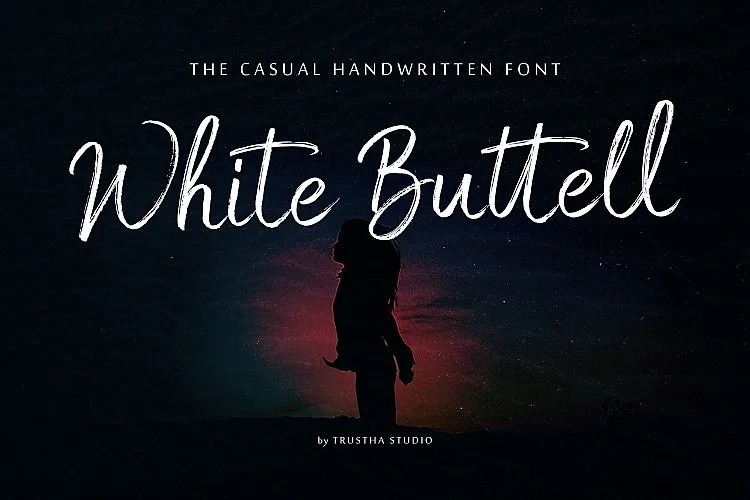
White Buttell Brush Font – Download Grátis
Olá! Aproveite essa descritiva introdução à White Buttell Brush Font. Para quem adora uma boa música, esta fonte é a perfeita melodia para seus designs, transmitindo um som mais alto ou apenas por ser incrível de se ver! Introduzimos White Buttell Font, que é uma fonte de script rascunho manual. Essa fonte tem um estilo natural da caneta secada, tornando-a perfeita para a criação de marca, anúncios, design de painéis, logotipos, capas de livros e revistas, embalagens, cabeçalhos de sites, cartões de convite, designs de roupas, produtos promocionais, campanhas de moda, newsletters, capas de álbuns e criações de citações. Com certeza, essa font será uma ótima adição a seu portfólio criativo.